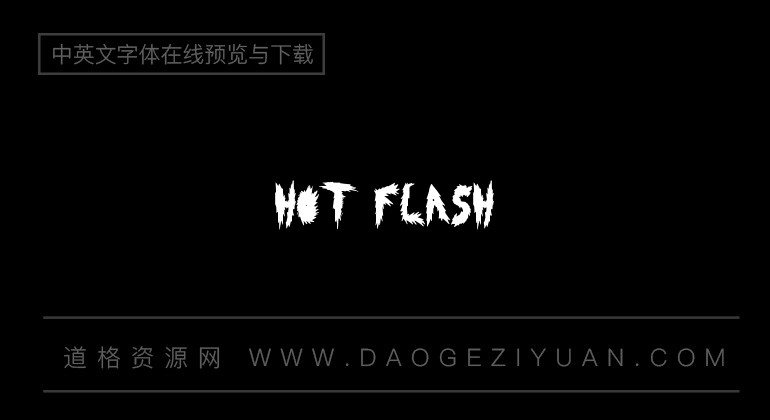
Hot Flash 是一种英文字体,由设计师 Hannes von Döhren 在 2010 年创建。它属于 sans-serif 字体家族,具有突出的高度和粗犷的笔画,使其在大标题和短语中非常适用。 Hot Flash 字体的特点是字母形状中有许多切割和倾斜的部分,这些元素的组合使得它具有非常鲜明的视觉效果。它的笔画粗细平衡,使得字体在大尺寸的应用中具有很好的可读性。 Hot Flash 字体的设计灵感来自于舞蹈和音乐节的海报设计。这种字体非常适合用于音乐、艺术和时尚等领域的设计项目,以及需要大胆和突出的视觉元素的设计。 总体而言,Hot Flash 字体是一种非常有趣和富有表现力的字体,在合适的设计中可以产生非常突出和引人注目的效果。内容介绍
Hot Flash是一款非常不错的手写艺术字体,具有很好的视觉感,适合于文化类的宣传设计、商业类品牌的广告和产品包装设计以及个性化文字排版等较多场景。